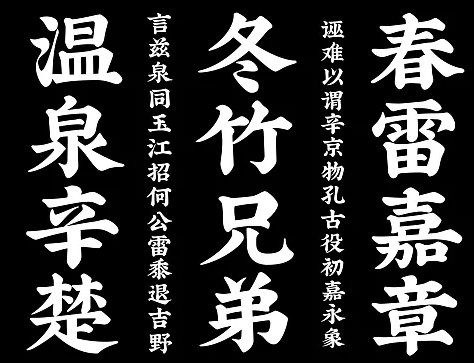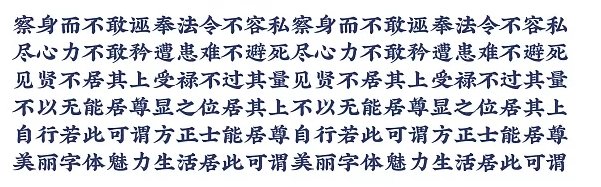
天宇招牌體是平面設(shè)計師葉天宇的首款字體,專為商品招牌而創(chuàng),采用大家熟悉的楷書字體,部分連貫的筆畫,讓文字更有質(zhì)感,風(fēng)格獨一韻味十足,喜歡的朋友不妨來綠色資源網(wǎng)欣賞吧!
此款字體追求一種樸實、誠懇、有親近感,但也還有點帥的氣質(zhì)。
為中式偏復(fù)古的標(biāo)題排布而做。僅做了200多字,敬請期待哦!
有的事情掙扎徘徊于生死傳承,有的事情悲慟感慨在價值貶落。
而我們的做字體呢,慶幸,字 不會消失。
字像水一樣,現(xiàn)代社會里沒有字,人不能活。
衷心希望我們街頭小店的招牌 能讓大家看到不一樣的氣質(zhì)。
做字的人,并不想把這個世界打造成某一種風(fēng)格,而是希望能給大家多一種選擇。
在此,給大家分享我現(xiàn)在做的《天宇招牌體:初回》。最初制作是參加方正獎評審,獲得入圍獎,我個人很喜歡。